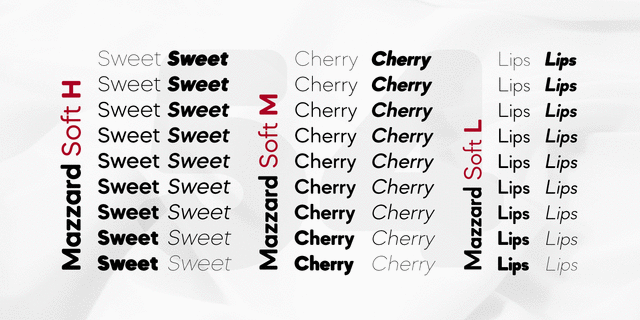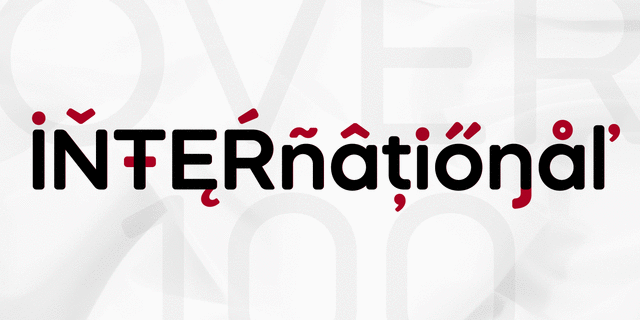
Mazzard Soft M – это часть шрифтового семейства Mazzard Soft, которое в свою очередь является версией с закруглёнными углами суперсемейства Mazzard. В этой версии есть ещё два геометрических гротеска, которые отличаются высотой строчных знаков (H и L).
Шрифт имеет широкий спектр языковой поддержки, включая кириллицу, и предлагает большой выбор альтернативных глифов.
Шрифт разработал Олег Лищук в 2019 году.